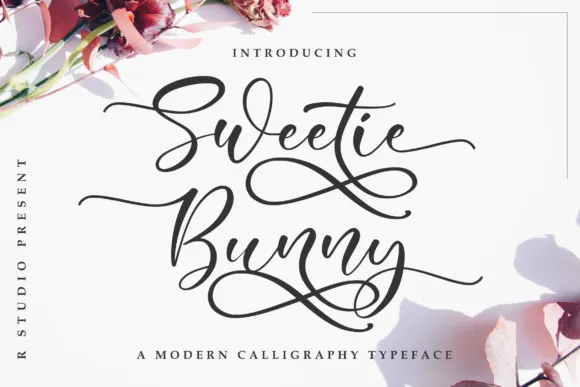
Sweetie Bunny Script Font – Download Grátis
Descubra Sweetie Bunny Font, uma linda e romântica fonte de script ideal para sua próxima criação visual. Este novo design, criado pela R. Studio na 1001fonts, traz um ar elegante com delicadas inclinações que aprimoram ainda mais seu estilo único. Perfeita para aplicações em logotipos, marcas, revistas, páginas web ou blogs, embalagens, cartões de convite e até mesmo anúncios para casamentos, Sweetie Bunny Font possui um charme fêmea que o torna ideal para diversos projetos. Ideal para aqueles que buscam uma fonte sofisticada com um toque romântico, ela é perfeita para estilos modernos de design. Com seu formato de escrever à mão, a Sweetie Bunny Font traz uma sensação única e única que se encaixa harmoniosamente em qualquer projeto visual. Enganche-se ao encanto desta fonte, uma verdadeira peça-chave para seus próximos trabalhos de design.